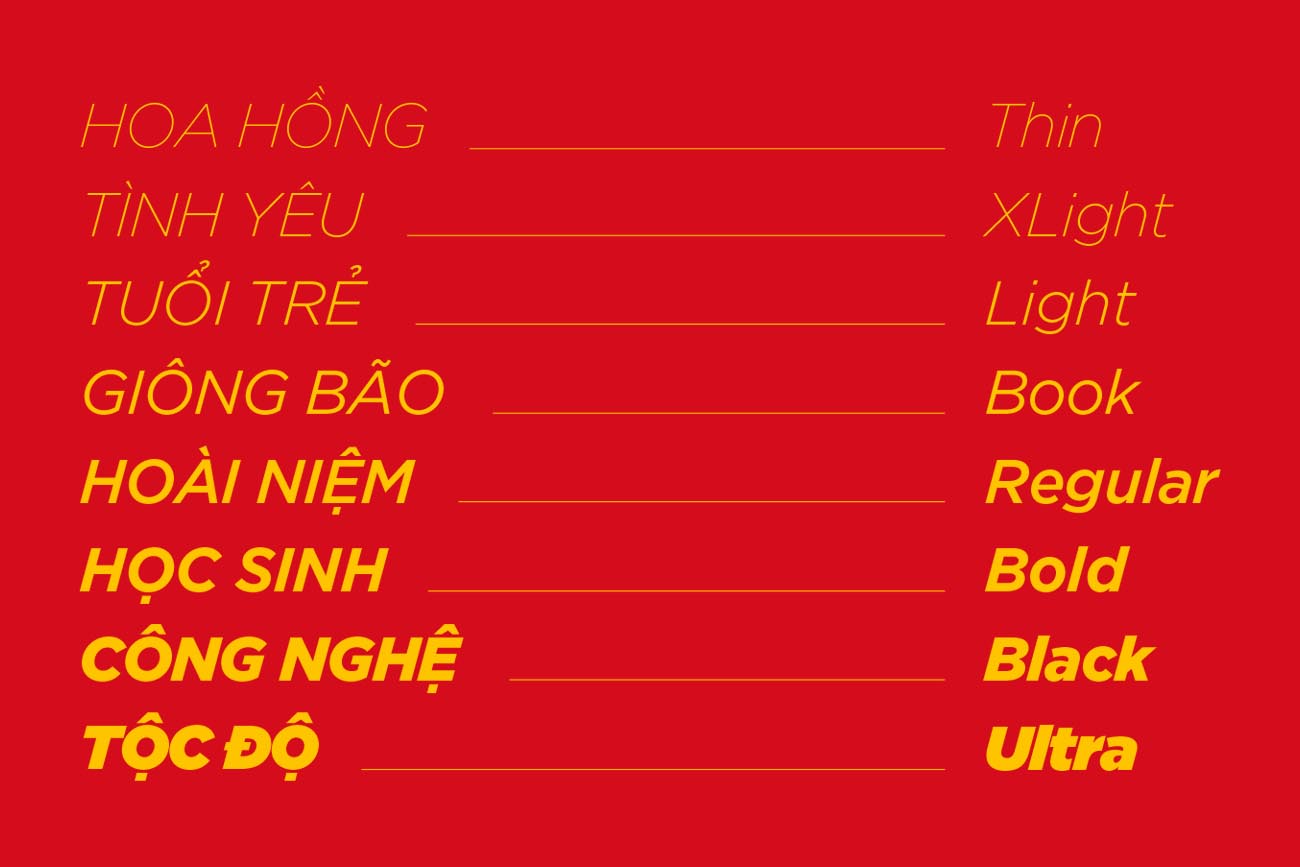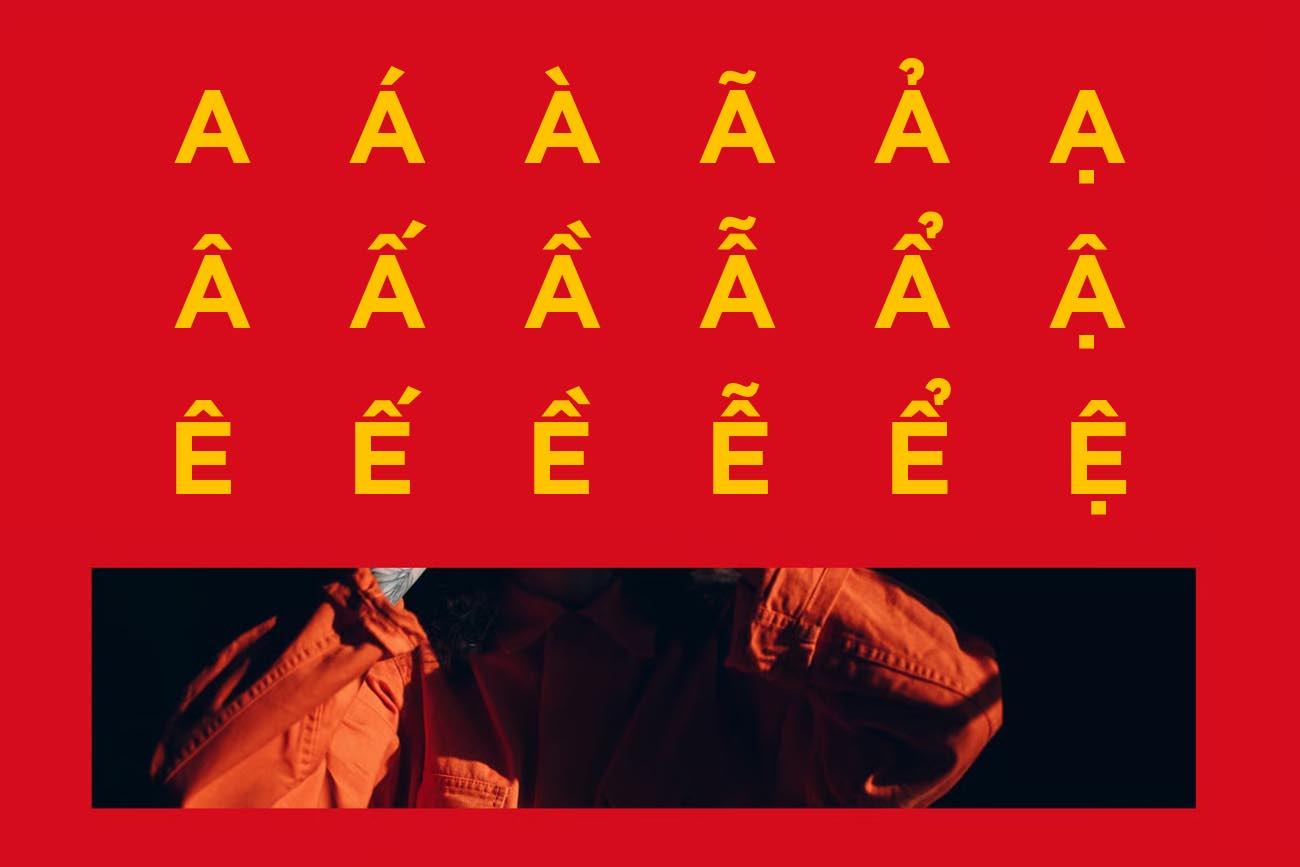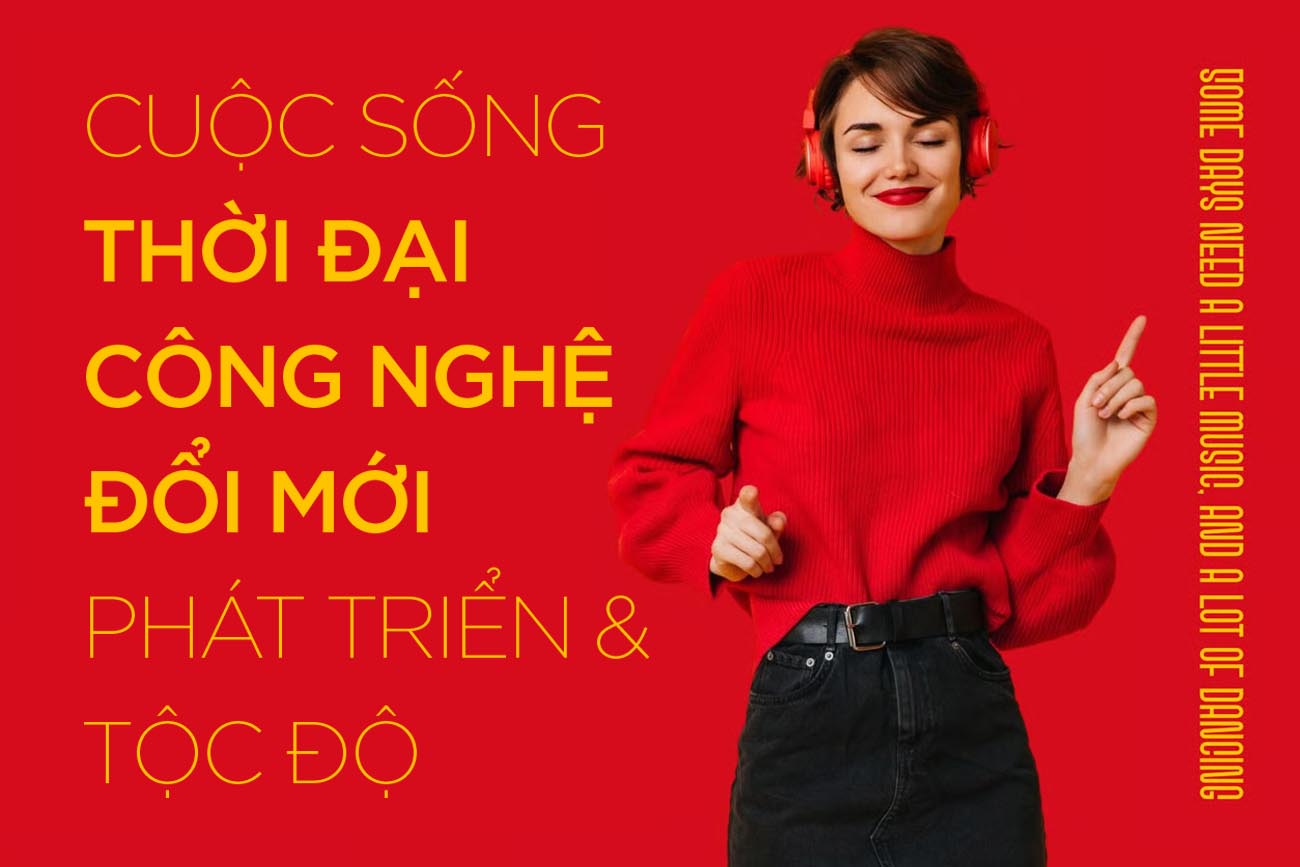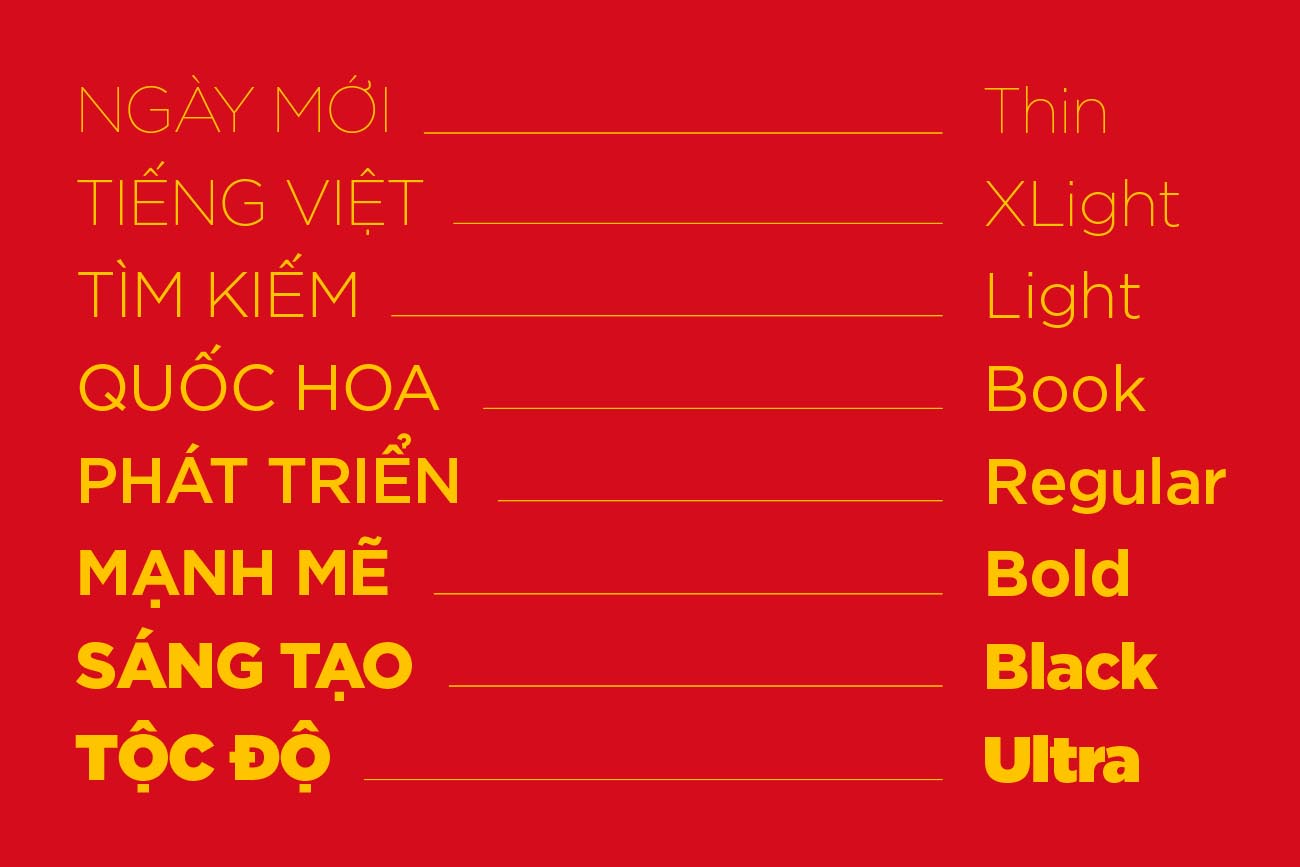
Tác giả Tobias Frere Jones
Việt hóa Team SVN
Bạn đang tìm kiếm một font chữ sans-serif hiện đại vừa mạnh mẽ, tối giản nhưng vẫn thể hiện sự chuyên nghiệp trong từng thiết kế? Font SVN Gotham Việt hóa chính là lựa chọn lý tưởng – đặc biệt dành cho nhà thiết kế cần một bộ font gọn gàng, dễ ứng dụng và hỗ trợ đầy đủ tiếng Việt.
Font SVN Gotham Là Gì?
Gotham là một trong những font chữ không chân nổi tiếng nhất thế giới, được thiết kế bởi Tobias Frere-Jones vào năm 2000. Lấy cảm hứng từ các bảng hiệu cổ điển trên đường phố New York, Gotham mang phong cách hình học cân đối, rõ ràng và cực kỳ dễ đọc.
Không chỉ xuất hiện trong chiến dịch tranh cử của Tổng thống Mỹ Barack Obama, Gotham còn được tin dùng trong hàng loạt thiết kế thương hiệu toàn cầu.
Phiên bản SVN Gotham Việt hóa là sản phẩm do nhóm SVN Type – một nhóm thiết kế font Việt hóa uy tín tại Việt Nam thực hiện. Bộ font đã được Việt hóa hoàn chỉnh, hỗ trợ đầy đủ dấu tiếng Việt, giữ nguyên vẻ hiện đại, sắc nét của bản gốc mà vẫn đảm bảo khả năng trình bày tiếng Việt chuyên nghiệp.
Bộ Font Gồm 16 Style Linh Hoạt
Font SVN Gotham Việt hóa bao gồm 16 style linh hoạt – chia đều giữa chữ thẳng và chữ nghiêng, phù hợp cho mọi ngữ cảnh thiết kế:
• Upright: Thin, XLight, Light, Book, Regular, Medium, Bold, Black
• Italic: Thin Italic, XLight Italic, Book Italic, Regular Italic, Medium Italic, Bold Italic, Black Italic
Các kiểu chữ được thiết kế nhất quán, giúp người dùng dễ dàng phối hợp trong một hệ thống thiết kế, từ in ấn đến kỹ thuật số.
Ưu Điểm Nổi Bật Của Font SVN Gotham Việt Hóa
• Hỗ trợ tiếng Việt đầy đủ: Bao gồm toàn bộ dấu thanh, chữ hoa – thường, ký tự mở rộng & ký hiệu đặc biệt.
• Thiết kế sans-serif hình học hiện đại: Cân đối, gọn gàng, dễ đọc ở mọi kích thước và nền tảng hiển thị.
• Đa dạng về trọng lượng & nghiêng/thẳng: Giúp bạn xây dựng hệ thống typographic bài bản cho mọi dự án.
Ứng Dụng Thực Tế
Font SVN Gotham Việt hóa phù hợp với nhiều mục đích thiết kế như:
• Thiết kế logo, bộ nhận diện thương hiệu
• Poster, banner quảng cáo, menu nhà hàng, tạp chí
• Slide thuyết trình chuyên nghiệp, giao diện web & mobile app
• Thiết kế video, thumbnail YouTube, nội dung mạng xã hội
Nhờ khả năng thích ứng cao và phong cách trung tính hiện đại, font này phù hợp cho cả dự án sáng tạo lẫn ứng dụng doanh nghiệp nghiêm túc.
Kết Luận
Font SVN Gotham Việt hóa là một trong những font chữ không chân mạnh mẽ và hiện đại nhất dành cho người dùng Việt. Với 16 style linh hoạt, khả năng hiển thị tiếng Việt xuất sắc và thiết kế hình học chuẩn mực, đây là lựa chọn đáng tin cậy cho mọi nhà thiết kế, marketer và doanh nghiệp.